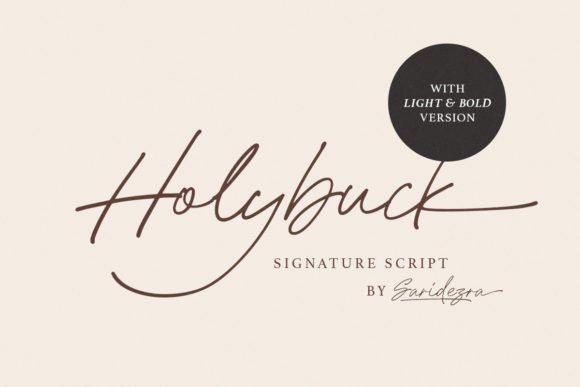
Creativefabrica Holybuck Font 2021
[Creativefabrica] Holybuck Font (2021)
Holybuck - это красивый и изысканный шрифт.
Он имеет стильный, элегантный и современный вид, который можно использовать для логотипов, брендинга, приглашений, канцелярских принадлежностей, свадебных дизайнов, постов в социальных сетях и многого другого!